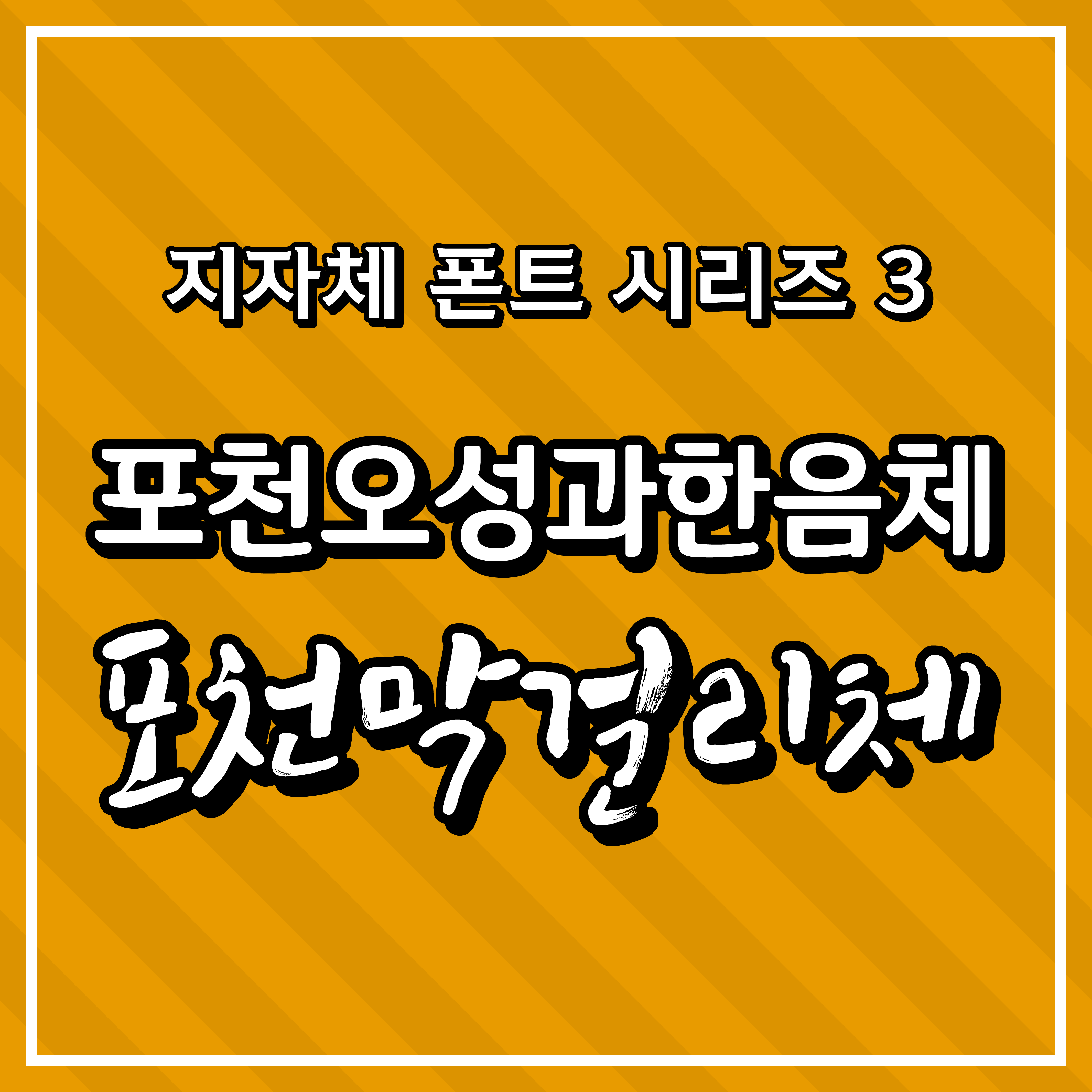
안녕하세요, 여러분! 지난 시리즈에서는 서울시와 김해시에서 제공하는 무료 폰트를 소개해 드렸는데요, 오늘은 경기도 포천시에서 탄생한 두 가지 독특한 폰트를 만나보겠습니다~
포천서체
포천시에서 제공하는 폰트는 총 두 가지입니다. 곧은 선비정신과 맑은 계곡이 가득한 포천을 표현한 '포천 오성과 한음체'와 80년 전통의 포천 막걸리와 무형문화재 술도가의 "장인정신"이 담긴 '포천 막걸리체'입니다.
폰트 패밀리
포천 오성과 한음체는 Regular와 Bold체를 지원합니다.
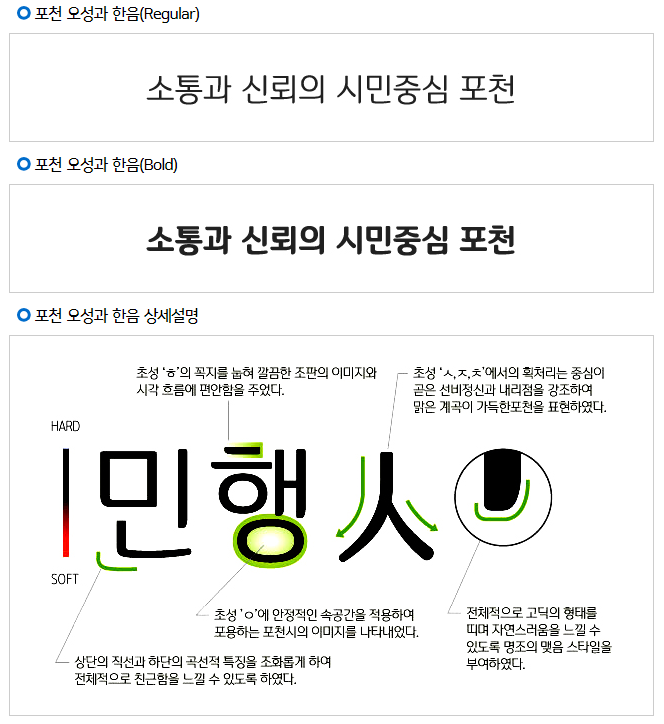
포천 막걸리체는 단일 폰트입니다.